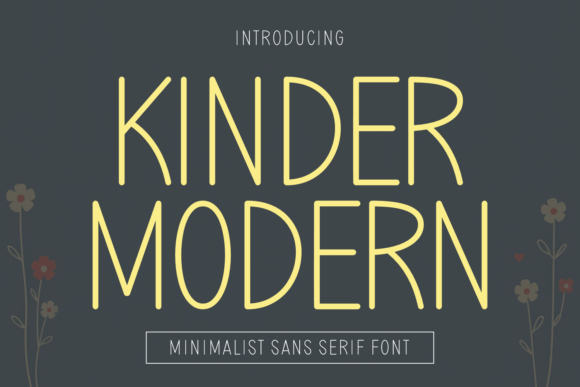
Kinder Modern
Kinder Modern – La police sans‑serif qui allie minimalisme et douceur
Vous recherchez une typographie à la fois moderne, lisible et charmante pour vos projets éducatifs ou votre branding ? Kinder Modern répond parfaitement à ces exigences. Ce font sans‑serif minimaliste se distingue par ses traits fins et monolignes, ainsi que par ses formes arrondies qui évoquent la convivialité enfantine tout en conservant une élégance épurée.
- Design épuré : des lignes monolignes ultra fines qui garantissent une clarté exceptionnelle, même à petite taille.
- Formes arrondies et amicales : chaque glyphe possède des courbes douces qui créent une atmosphère accueillante, idéale pour les supports destinés aux enfants.
- Excellente lisibilité : la structure simple de Kinder Modern assure une lecture fluide sur papier comme sur écran, quel que soit le format.
- Polyvalence d’utilisation : parfait pour les manuels scolaires, les décors de nurseries modernes, les logos de marques « clean‑cut » et tout projet nécessitant une touche contemporaine et délicate.
- Compatibilité multilingue : le jeu de caractères couvre les alphabets latins courants, facilitant son intégration dans des projets multilingues.
En résumé, Kinder Modern est le choix idéal pour quiconque veut allier minimalisme et chaleur humaine. Que vous conceviez du matériel éducatif, une signalétique de crèche, ou une identité visuelle épurée, cette police apporte une touche de sophistication douce qui capte l’attention tout en restant discrète.
Pourquoi choisir Kinder Modern pour votre prochain projet ?
- Facile à associer avec d’autres polices grâce à son style neutre.
- Optimisée pour le web et l’impression, garantissant un rendu net sur tous les supports.
- Renforce la perception d’une marque moderne, fiable et proche des enfants.
Adoptez Kinder Modern dès aujourd’hui et donnez à vos créations une allure à la fois légère et haut de gamme !